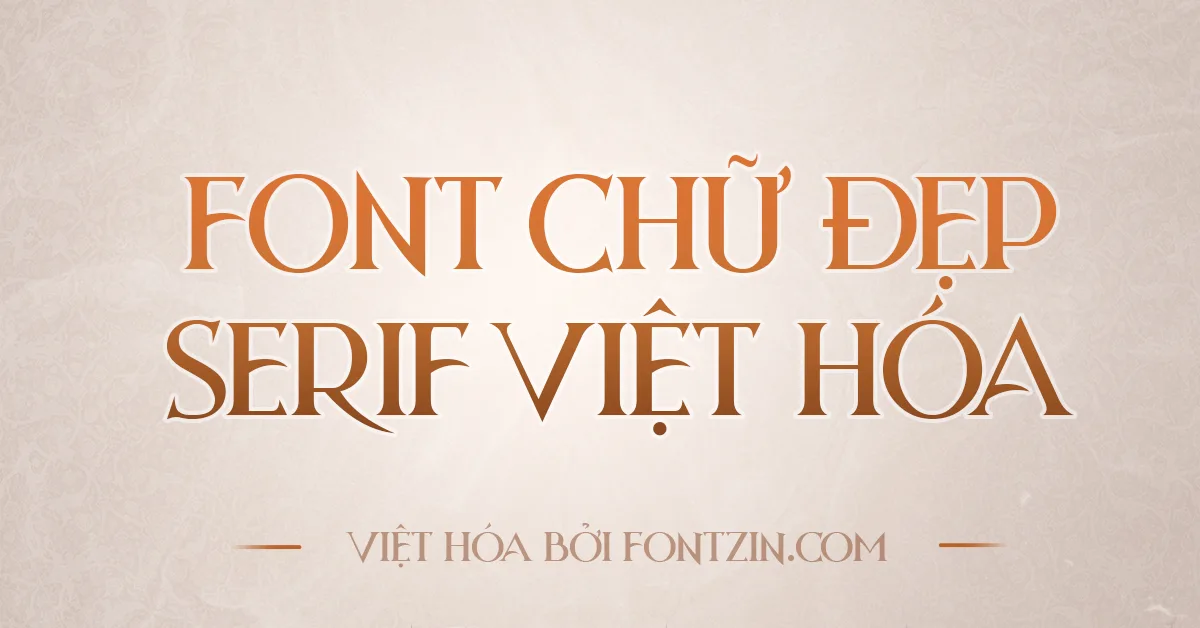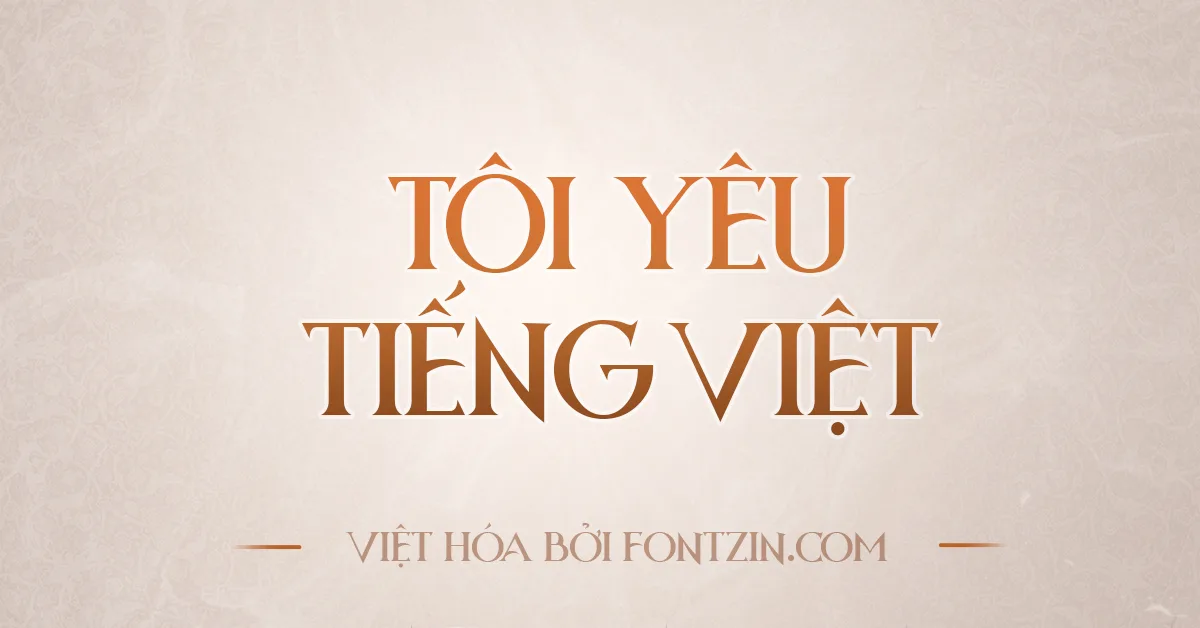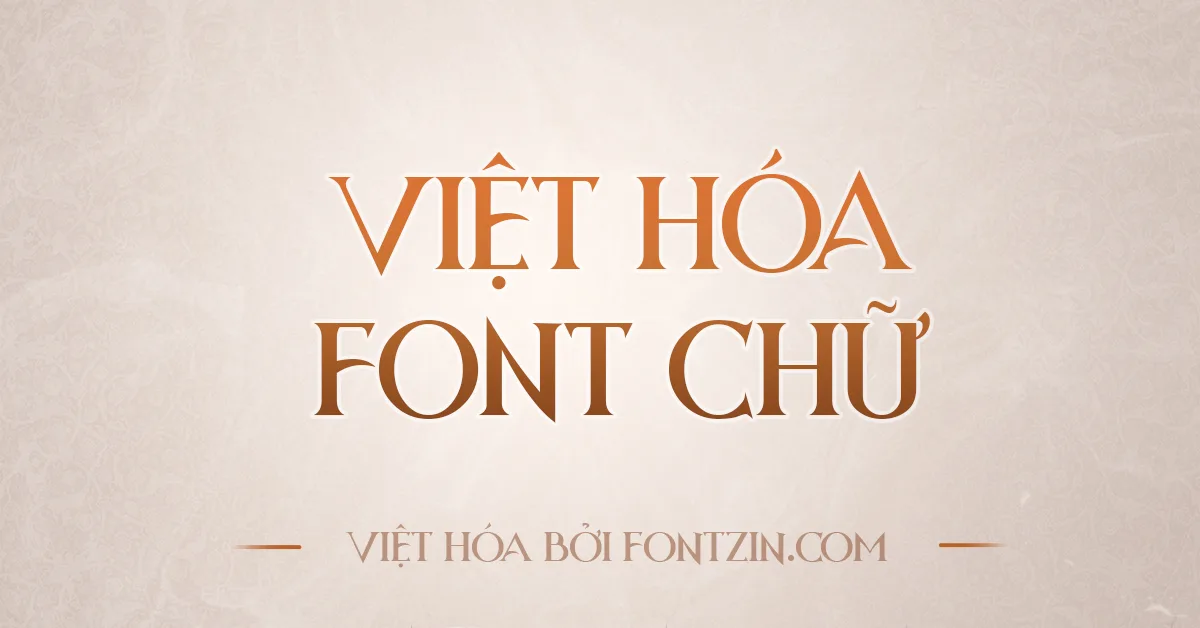
Font Fz Strange Dreams Việt hóa
Font Fz Strange Dreams Việt hóa – Phông chữ đầy biểu cảm và cá tính
Font Fz Strange Dreams Việt Hóa là một phông chữ độc đáo với nét thiết kế táo bạo, mang lại cảm giác vừa kỳ ảo vừa đầy cá tính. Đúng như tên gọi, Fz Strange Dreams gợi lên sự liên tưởng đến những giấc mơ kỳ lạ, với những đường nét sáng tạo không theo lối mòn. Phông chữ này có phong cách pha trộn giữa sự phóng khoáng và phá cách, tạo nên một diện mạo đầy cảm xúc và biểu cảm.
Với thiết kế độc đáo và ấn tượng, Fz Strange Dreams rất phù hợp cho những dự án sáng tạo, như thiết kế bìa sách, poster, hay các dự án quảng cáo mang tính nghệ thuật cao. Các đường nét của phông chữ tạo nên một sức hút mạnh mẽ, giúp nội dung dễ dàng nổi bật và truyền tải thông điệp một cách táo bạo và ấn tượng.
Phiên bản Việt hóa của Fz Strange Dreams hỗ trợ đầy đủ các ký tự tiếng Việt, giúp bạn dễ dàng sử dụng trong các dự án sáng tạo với ngôn ngữ bản địa. Điều này mang lại sự tiện lợi mà không làm mất đi sự độc đáo và cá tính của phông chữ.
Fz Strange Dreams Việt Hóa là lựa chọn hoàn hảo cho những ai đang tìm kiếm một phông chữ mới lạ, đầy biểu cảm và muốn tạo nên dấu ấn đặc biệt trong các sản phẩm thiết kế của mình.